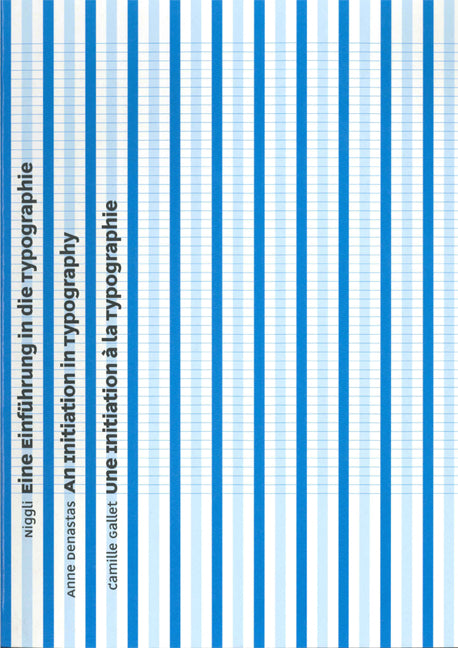
Eine Einführung in die Typographie / An Initiation in Typography / Une Initiation à la Typographie
Diese raffiniert gestaltete Einführung in die Typographie beginnt mit einem grossen Massstab, den Proportionen im Weltall, und endet mit dem kleinsten typografischen Massstab, den Schriften. Geschickt führen die Autorinnen in die Welt der visuellen Gestaltung und Typografie ein, wecken durch eine ausgeklügelte Ästhetik die Neugier des Lesers und erschliessen Seite für Seite die Magie der Typografie. Bestechend kurze und prägnante Texte führen in die jeweilige Thematik ein; typografische Probleme werden durch einfache geometrische Formen dargestellt. Das erste Kapitel beschäftigt sich mit den Fragen der Proportionen: mathematische Systeme, goldener Schnitt, Papierformate, Rastersysteme, typografische Masseinheiten. Das zweite Kapitel thematisiert die Spannung von Schwarz und Weiss: Gestaltungsprobleme, Prinzipien der Satzgestaltung und die Harmonie von Schwarz und Weiss. Das dritte Kapitel widmet sich den Einzelheiten: Ursprung der Buchstabenformen, Schriftfamilien und historische Schriften. Durch die Verwendung eines leicht transparenten Papiers wird die Wirkung eines Rastersystems deutlich. Diese Durchsichtigkeit lässt auf jeder Seite ein anderes Muster entstehen – ein bemerkenswert anderes Typografiebuch.